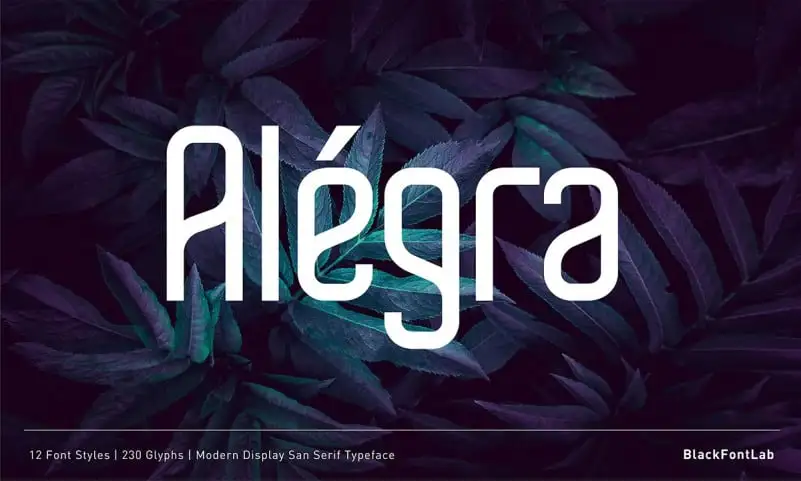
A Alégra Sans Serif é uma fonte moderna criada por BlackFontLab, projetada para oferecer várias opções de estilo, adequadas para desde o texto corporal até títulos grandes e desde estilos clássicos até as mais atuais e brilhantes. Esta família tipográfica minimalistamente se inspira em um estilo futurista natural, perfeitamente adaptável para apresentações, exibições ou qualquer tipo de projeto que busque uma beleza única. A Alégra Sans Serif possui uma aparência curvilínea leve e formal ao mesmo tempo estilosa, tornando-a ideal para projetos que desejam um look atraente e sofisticado. Preparamos 12 diferentes opções de estilo, incluindo linhas finas, leves, regulares, médias, negritos, bold solar e todas suas versões em itálico. Com sua curva suave e formas distintivas, essa fonte oferece uma aparência elegante sem perder a modernidade. Para aqueles que buscam uma nova opção para seus projetos gráficos, a Alégra Sans Serif é uma escolha perfeita, disponível no catálogo de fontes da BlackFontLab.